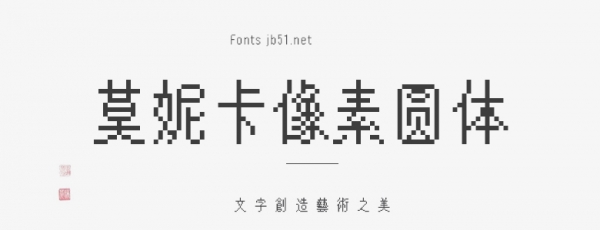
追求由像素形成的曲線美。
兼具“柔和”和“嚴(yán)肅”的像素字體。
完整記錄 JIS 1 級漢字 2965 和 2 級漢字 3390!
它還支持打印標(biāo)準(zhǔn)字體 1022 個字符。
美麗的歐洲語言和全面的多語言支持。
支持多種使用拉丁文和西里爾文的語言。
獨特的字符間距調(diào)整,即使在沒有字距調(diào)整功能的游戲開發(fā)環(huán)境中,也能實現(xiàn)自然美觀的歐式顯示。